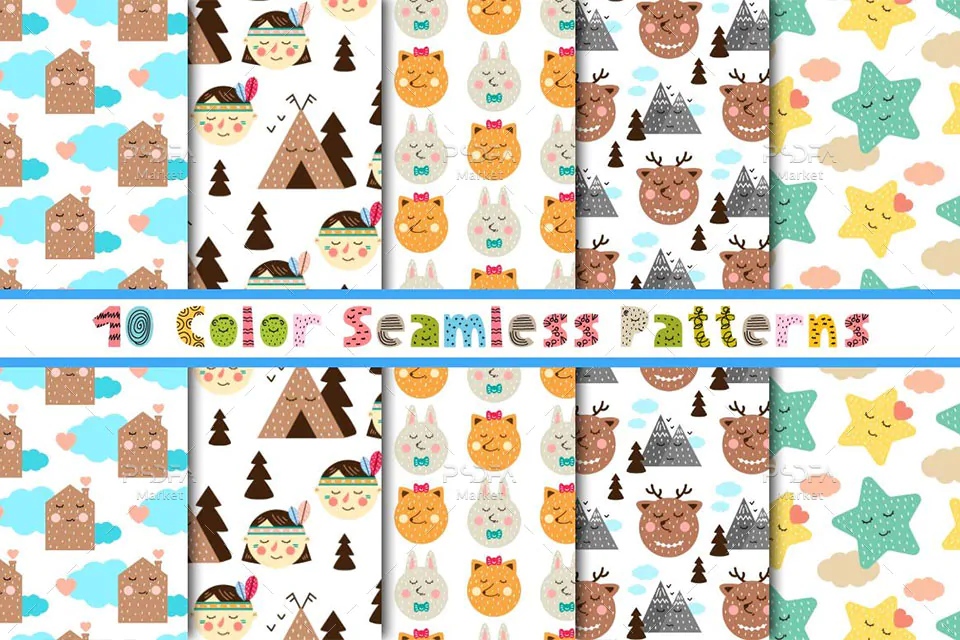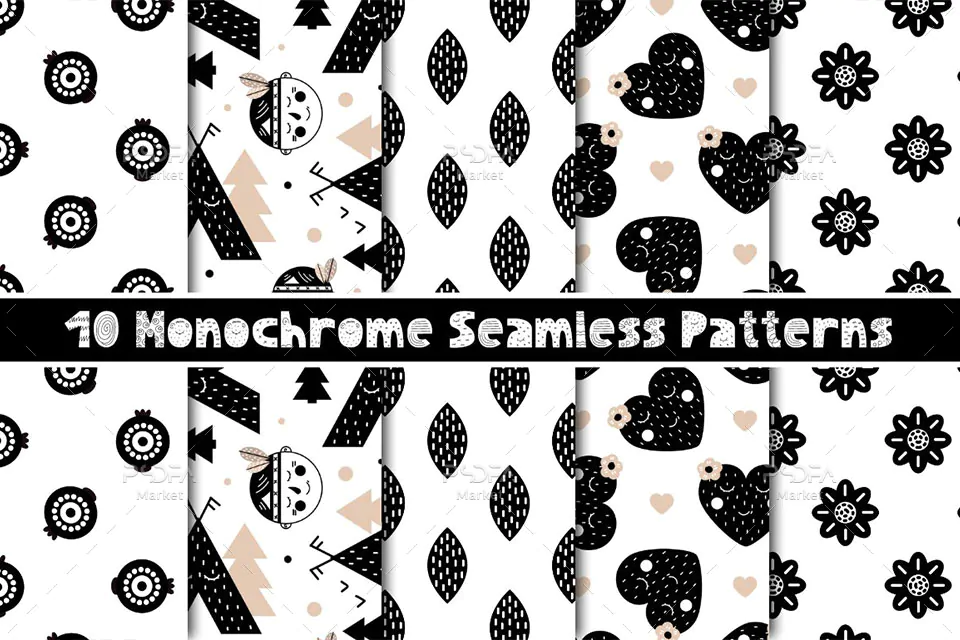
فونت فانتزی رنگی Lazy Olov و عناصر طراحی کودکانه مجموعه و کیتی فوق العاده زیبا از فونت انگلیسی کودکانه به همراه 10 پترن بدون درز، 10 پوستر و 15 عنصر طراحی است که به صورت وکتور طراحی شدهاند و مناسب جهت استفاده در طرح و پروژههای گرافیکی مختلف میباشند. این مجموعه عنصر طراحی و فونت رنگی Lazy Olov در قالب فایلهای eps, otf, png در فایل محصول قرار دارند که با نصب فایلهای otf در پوشه فونتهای سیستم میتوانید از این فونت زیبا در تمام نرم افزارهای گرافیکی و ویرایشگر متن استفاده کنید.
فونت فانتزی و کودکانه Lazy Olov در وزن معمولی (Regular) و در 3 سبک مختلف طراحی شده است که میتوانید از آن و این مجموعه طرح وکتور و کلیپ آرت فانتزی در طراحی انواع کارت تبریک، کارت پستال، لوازم التحریر، ظروف یکبار مصرف، بسته بندی محصولات، تقویم، دیزاین اتاق کودک، پوستر، قاب و کاور موبایل، بگهای خرید و هدیه، قاب عکس و صدها ایده دیگر استفاده کنید.
- وزن فونت: معمولی (Regular)